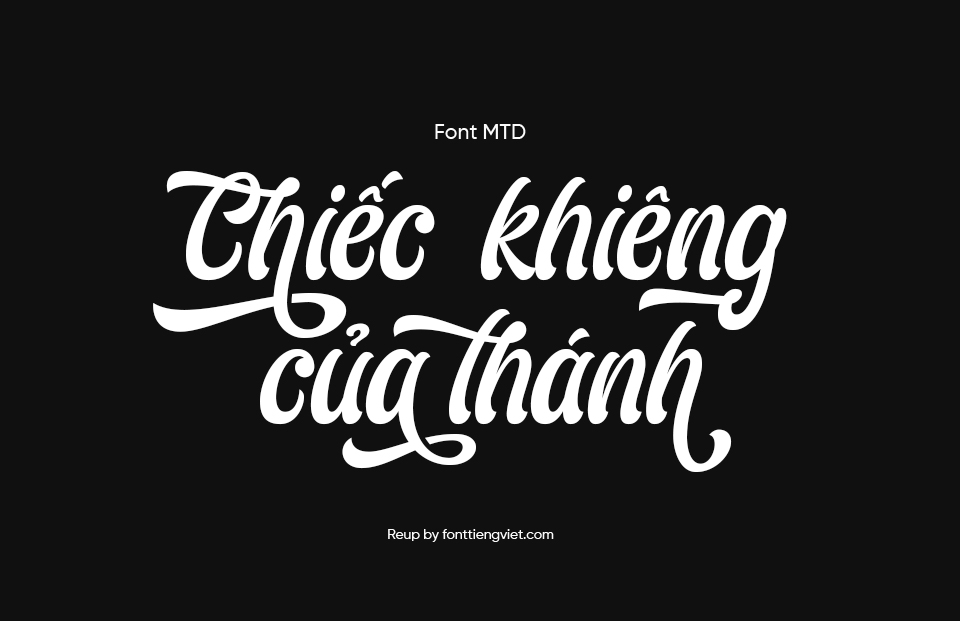
Font Việt hóa MTD Ariestha – Lựa chọn hoàn hảo cho thiết kế bay bổng
Giới thiệu về Font Việt hóa MTD Ariestha
Trong thế giới sáng tạo, việc tìm kiếm một Font Chữ vừa mang nét nghệ thuật vừa đảm bảo tính ứng dụng là điều vô cùng quan trọng. Font Việt hóa MTD Ariestha chính là giải pháp lý tưởng cho những ai đang tìm kiếm sự nhẹ nhàng, thanh thoát và đầy nữ tính. Đây là một bộ font Script theo phong cách thủ công, mô phỏng những nét chữ viết tay mềm mại, giúp các bản thiết kế trở nên có hồn và gần gũi hơn với người xem. Phiên bản Việt hóa bởi MTD giúp người dùng dễ dàng sử dụng trong các phần mềm thiết kế mà không lo lỗi dấu tiếng Việt.
Đặc điểm nổi bật của MTD Ariestha
Bộ Font Việt hóa MTD Ariestha sở hữu những đường nét uốn lượn tự nhiên, tạo cảm giác như được vẽ bằng cọ thư pháp hiện đại. Các ký tự được chăm chút tỉ mỉ với độ dày mảnh đan xen nhịp nhàng, mang lại sự cân đối thị giác tuyệt vời. Đặc biệt, bộ font này cung cấp nhiều ký tự thay thế (alternates) và các đường gạch chân trang trí, giúp bạn thỏa sức sáng tạo mà không bị gò bó. Sự kết hợp giữa phong cách hiện đại và cổ điển khiến nó trở nên linh hoạt trong nhiều bối cảnh khác nhau.
Ứng dụng thực tế của font chữ
Nhờ vẻ ngoài tinh tế, Font Việt hóa MTD Ariestha cực kỳ phù hợp cho các thiết kế thiệp cưới, bìa sách, nhãn hàng mỹ phẩm hoặc các bài đăng trên mạng xã hội. Đối với học sinh và giáo viên, bộ font này có thể dùng để trang trí bài giảng điện tử hoặc làm tiêu đề cho các báo tường, mang lại sự sinh động và thu hút. Khả năng hiển thị mượt mà giúp thông điệp truyền tải trở nên ngọt ngào và chân thực hơn bao giờ hết.